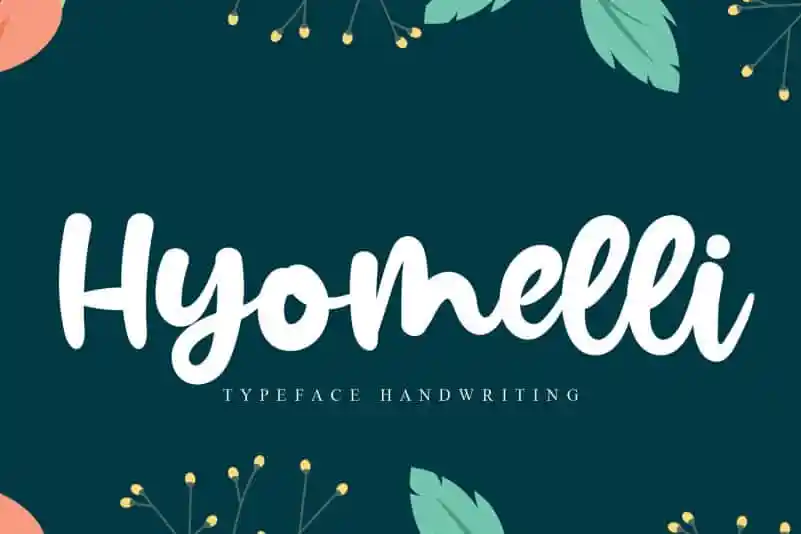
Hyomelli Script Font – Fonte Grátis
Hyomelli Script Font
Hyomelli Script Font é uma elegante fónta escrita a mão que transmite seriedade e fluidez. Inspirada no estilo dos desenhos de crianças, essa fonte tem um toque leve e descontraído que se destaca em contextos diversos. Suas características fluidas combinadas com traços distintivos criam uma imagem vibrante e envolvente. Hyomelli Script é uma escolha ideal para designers buscando estilos únicos capazes de se destacar, seja para um logotipo impactante ou para textos mais leves em uma publicação. Ideal para aqueles que buscam uma fonte script com toques distintivos e adaptáveis a uma variedade de cenários, Hyomelli Script é certamente um recurso indispensável no seu arsenal de ferramentas gráficas.